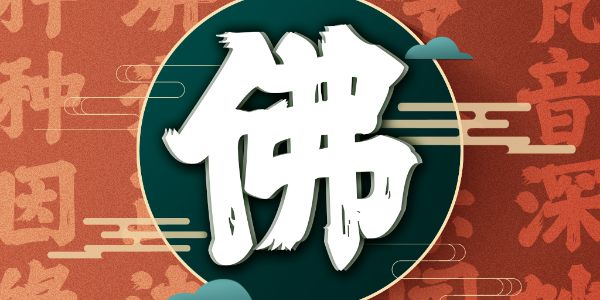
是什么样的LOGO要修改20次才定稿?
《黑神话:悟空》的LOGO以魔幻与中国风两个关键展开设计,运用夸张的江湖字体,边缘线条肆意不羁,形成了一种破空斩击的冲击感,每一笔一划都仿佛蕴含着不受拘束、放荡不羁、敢于挑战天地的性格特点。
你可能不知道的是——LOGO的设计经过20多次尝试、筛选,才有了有着孙悟空驾筋斗云那种潇洒肆意的最终版本。
其中"悟"字的设计,仿佛孙悟空手持金箍棒,踏碎凌霄,这个LOGO将悟空放荡不羁的感觉诠释得很完美。
这个LOGO的设计者,正是汉仪黄科榜书、汉仪黄科行书、汉仪黄科壮隶字体的作者:黄科。他也曾为《逆水寒》《流星蝴蝶剑》《仙剑世界》《三国谋定天下》《逆战未来》《御甲凌云志》等多款游戏题写LOGO。
让我们看看黄科老师是如何看待游戏与书法字体之间的结合的吧!
Q:书法与游戏的结合有什么现实意义?
A:现在的游戏与20年前的游戏已经有了本质的区别。不再是单纯的娱乐属性,只是解压或者打发时间那么简单。而是具备了对特定人群的知识普及教育,人际关系协调能力形成和审美引导的社会功能。比如一些国风游戏里包含中国历史,服饰文化,神话故事脉络,古人生活起居习惯的变迁等等。所以,好的书法字体对游戏本身是一个加持,使得国风游戏的形式跟内容更加的契合,审美上也能有所提升。另外,在书法推广层面,让更多的年轻人对书法有一个更直观的了解,喜欢甚至去主动去学习,这对书法艺术的推广也有非常积极地作用。
黄科老师题写的其他游戏logo
Q:您参与过许多游戏LOGO的创作,这些游戏的LOGO是不是一挥而就写成的?
A:一个游戏LOGO的诞生,跟大家想象中的拿起笔蘸上墨,几分钟就搞定是完全不一样的。
我们会先了解这个游戏项目的世界观,画面视觉风格,受众群体,对标或者近似风格游戏的参考。根据这些信息内容我会写十稿、二十稿,然后我们内部再选出不同风格的五稿,做好提案给到甲方。甲方根据这个五稿内容和游戏的风格来选出一到两稿的意向稿,我们再在意向稿上进行这个微调修改,比如修改一些字的辨识度,应用规范,解决后期制作的工艺问题,或者调整视觉风格导向问题,最后定出一稿进行精修加局部调整,直至完成定稿。
所以一个LOGO的诞生就是一个一来一回反复多轮的磨合过程。时间短则一个月慢则两三个月。绝不是写个字的功夫。
悟空logo提案稿
Q:之前您在B站上发过一个视频,大概是《黑神话》LOGO的演变,全部加起来差不多有20多种,为什么最后确定下现在的这版字?
A:第一从形态上,它其实有点具象化,就像是悟空脚踩金箍棒,手指前方动态感非常强。从意义上来说,他更像是在传达悟空直面天命,为战而生的一种信念。
第二,这个LOGO用的是毛笔去书写,整体的感觉就更飘逸,随机感很强。它所有的边缘线条,都是不可控的,具有一个很大的偶然性。那么最后形成一个这种剪影的效果,可以说都是机缘巧合。
所以我们一般会根据感觉来写很多稿,第一步内部筛选,第二步再让游科去筛选。综合来说,从形、意到最后实际落地等各个层面,最后也是一个缘分就能沉淀的。
Q:您觉得书法与商业之间的关系是什么?
A:商业书法跟传统书法艺术本质上是大相径庭的,二者只是在表现形式和使用工具上一致。
书法是一个很唯我的艺术形式,说白了就是要自己喜欢,写自己喜欢的东西,有独立的理论和审美体系,是一个二维的视觉呈现。
商业书法则恰好相反,商业书法是唯他的,首要考虑的是市场,是受众人群,是甲方在意的各种风格、视觉、应用场景等。不同受众的审美认知和对书法的认知天差地别,商书法要在他们的审美基础上略往上提升,达到一定的引导作用,而不是一味去迎合。视觉呈现上则有二维平面,三维动画,实物制作等多种样式。即便是最简单的二维平面展示也需要跟游戏内容,底纹图案做一个融合。